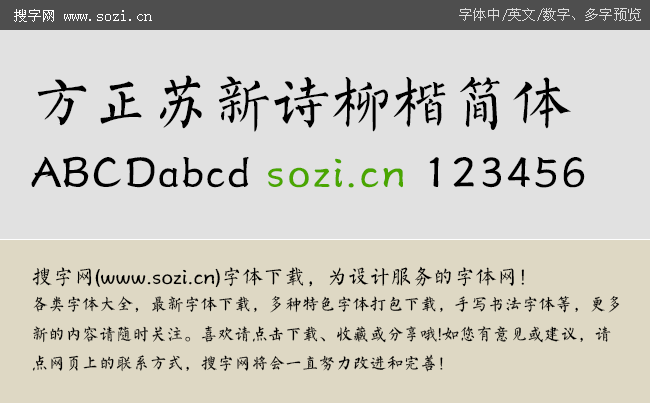
方正蘇新詩(shī)柳楷簡(jiǎn)體完美版
搜字網(wǎng)為大家提供一款方正蘇新詩(shī)柳楷體書(shū)法字體下載,方正蘇新詩(shī)柳楷體是一款手寫(xiě)楷體書(shū)法字體,字形大方美觀,筆畫(huà)棱角分明,可以應(yīng)用于平面廣告、名家題字、 藝術(shù)繪畫(huà)等領(lǐng)域,喜歡的用戶(hù)可下載收藏。